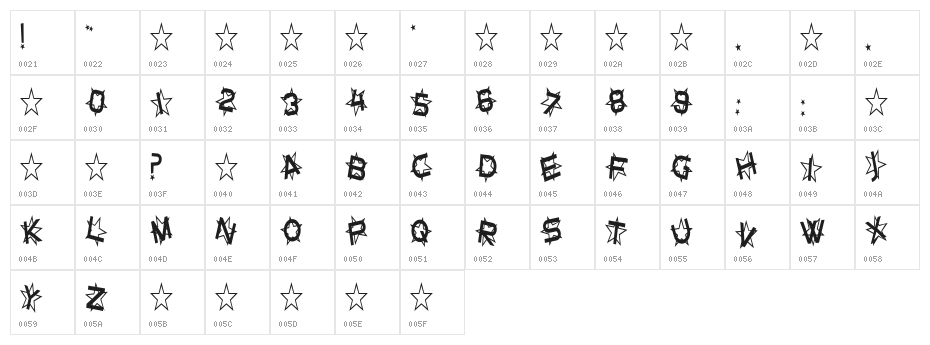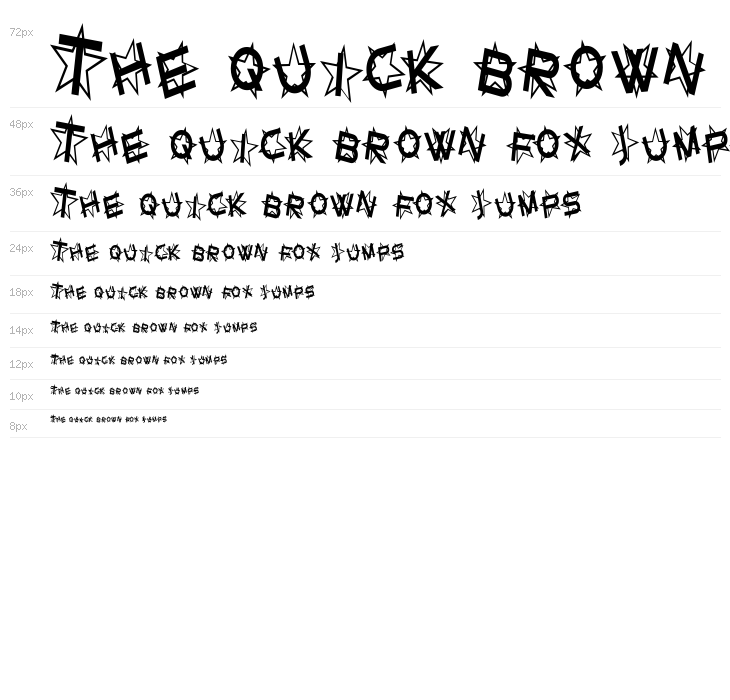
Star Dust Condensed Font
| Progetti proposti | Ideal for music album covers, event posters, themed party invitations, or any project needing a bold, eye-catching design. |